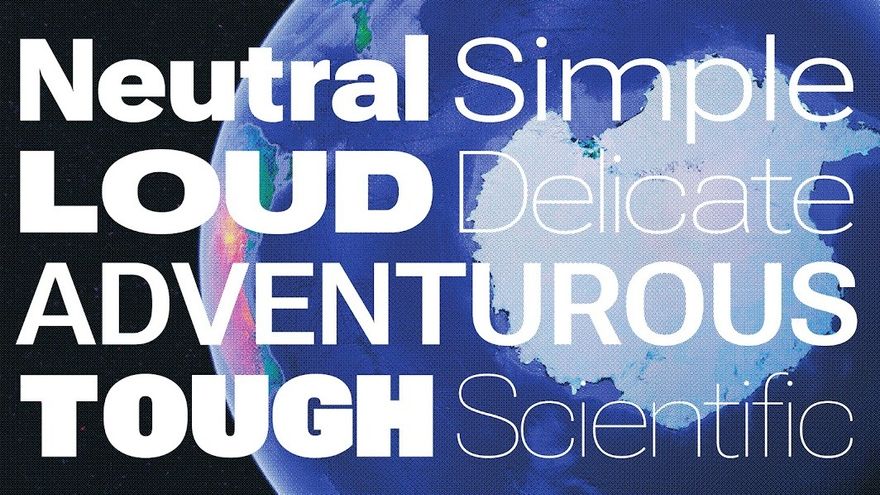
Самые популярные шрифты получили свое долгожданное и весьма логичное обновление. Дизайнеры получили еще больше возможности настраивать шрифты San Francisco и Roboto под себя.
San Francisco (SF Pro) variable
Новейшие системные шрифты Apple San Francisco, поставляемые с последними обновлениями macOS, охватывают гораздо более широкий диапазон веса и ширины, чем когда-либо прежде, а также оси для изменения оптического размера и мультиплексированных градаций.
Roboto Flex
Roboto — самая популярная загрузка Google Fonts. Впервые он был выпущен еще в 2011 году, но с годами он обновлялся, чтобы улучшить языковую поддержку и эстетические качества. Используется во всех продуктах Google и является бесплтаным.
Теперь к линейке присоединился еще один Roboto: Roboto Flex — серьезное обновление Roboto и крупнейшего проекта Google Fonts на сегодняшний день. Благодаря огромному диапазону веса и ширины оптических размеров, а также дополнительным возможностям для точной настройки, Roboto Flex был разработан Font Bureau , чтобы быть сверхмасштабируемым, адаптируемым, настраиваемым и оптимизируемым.